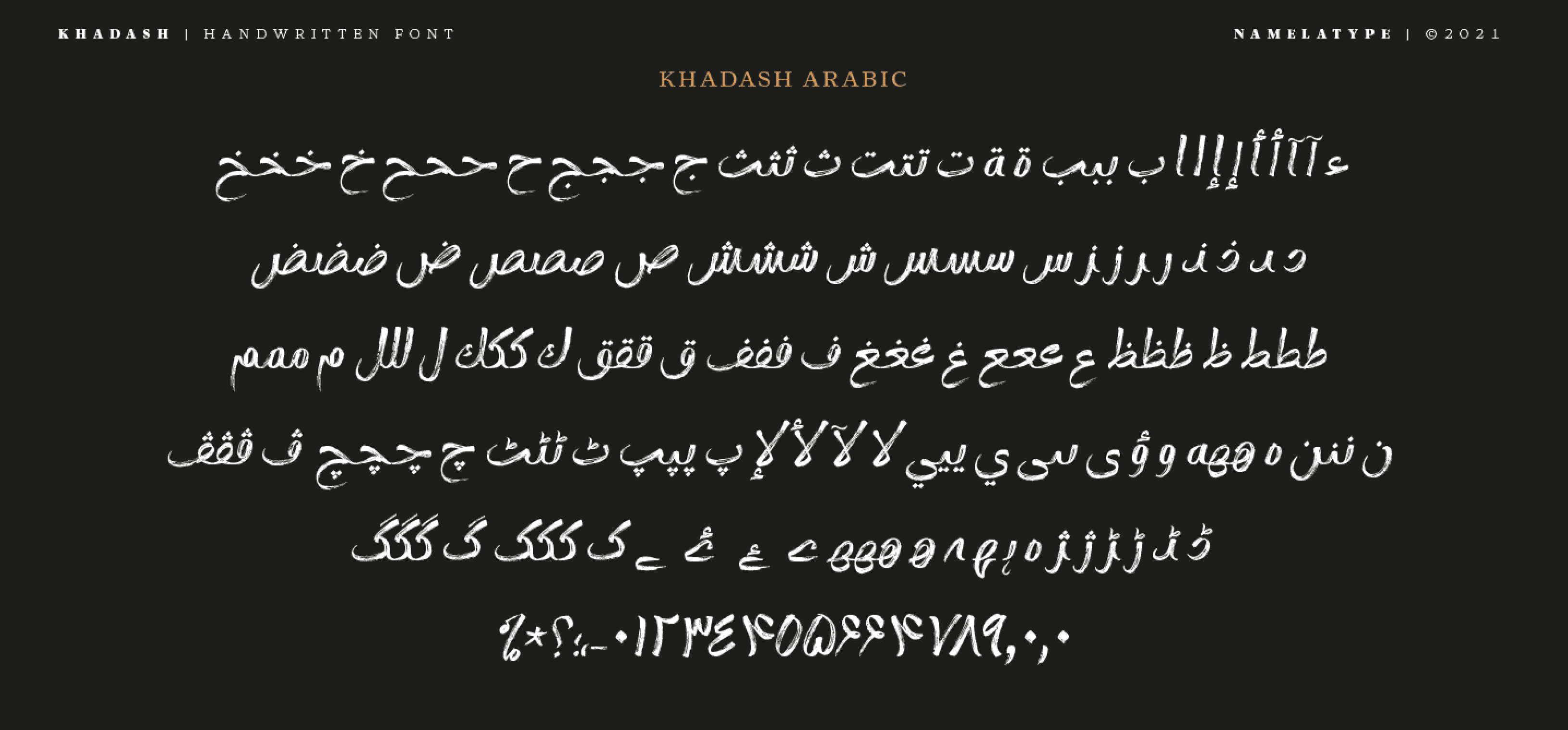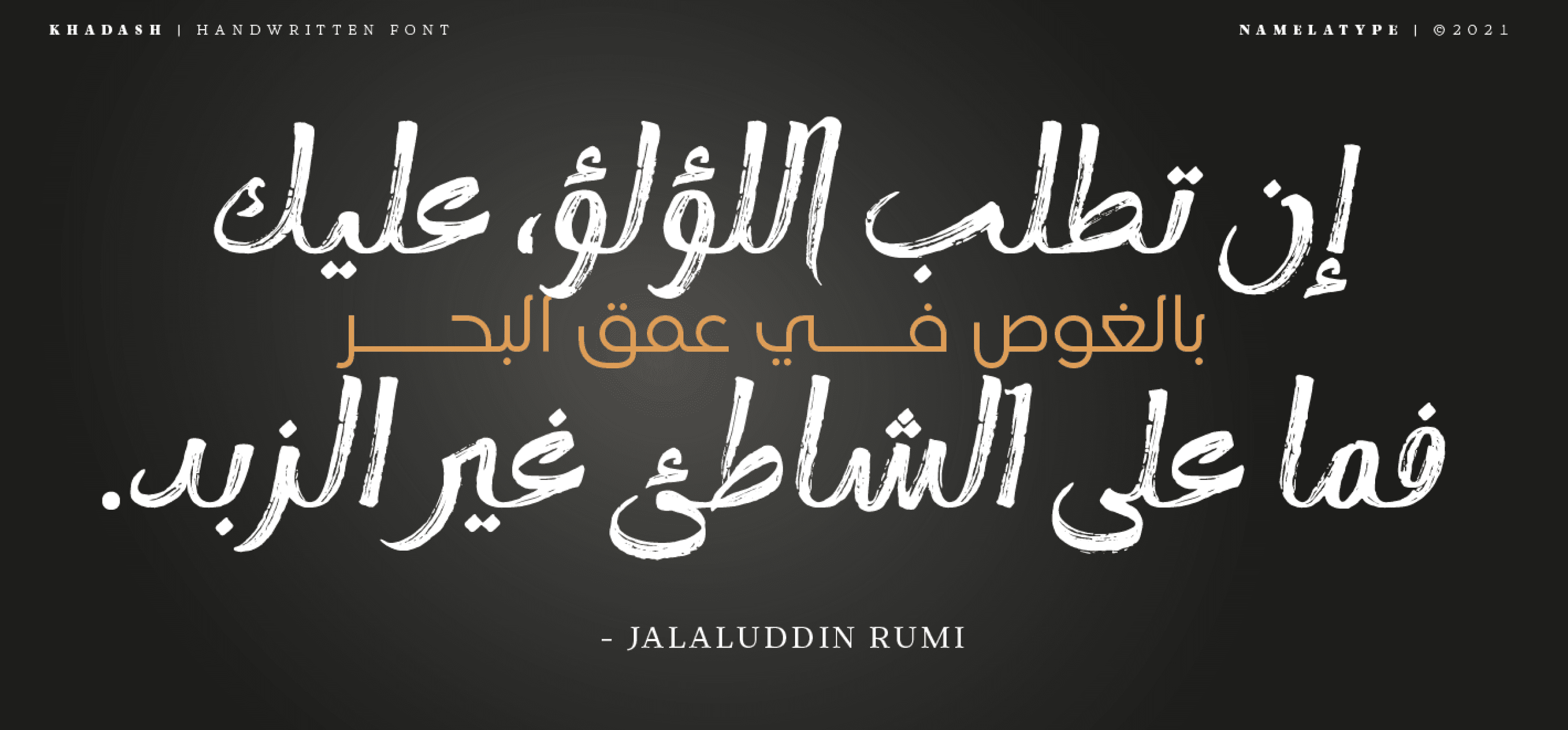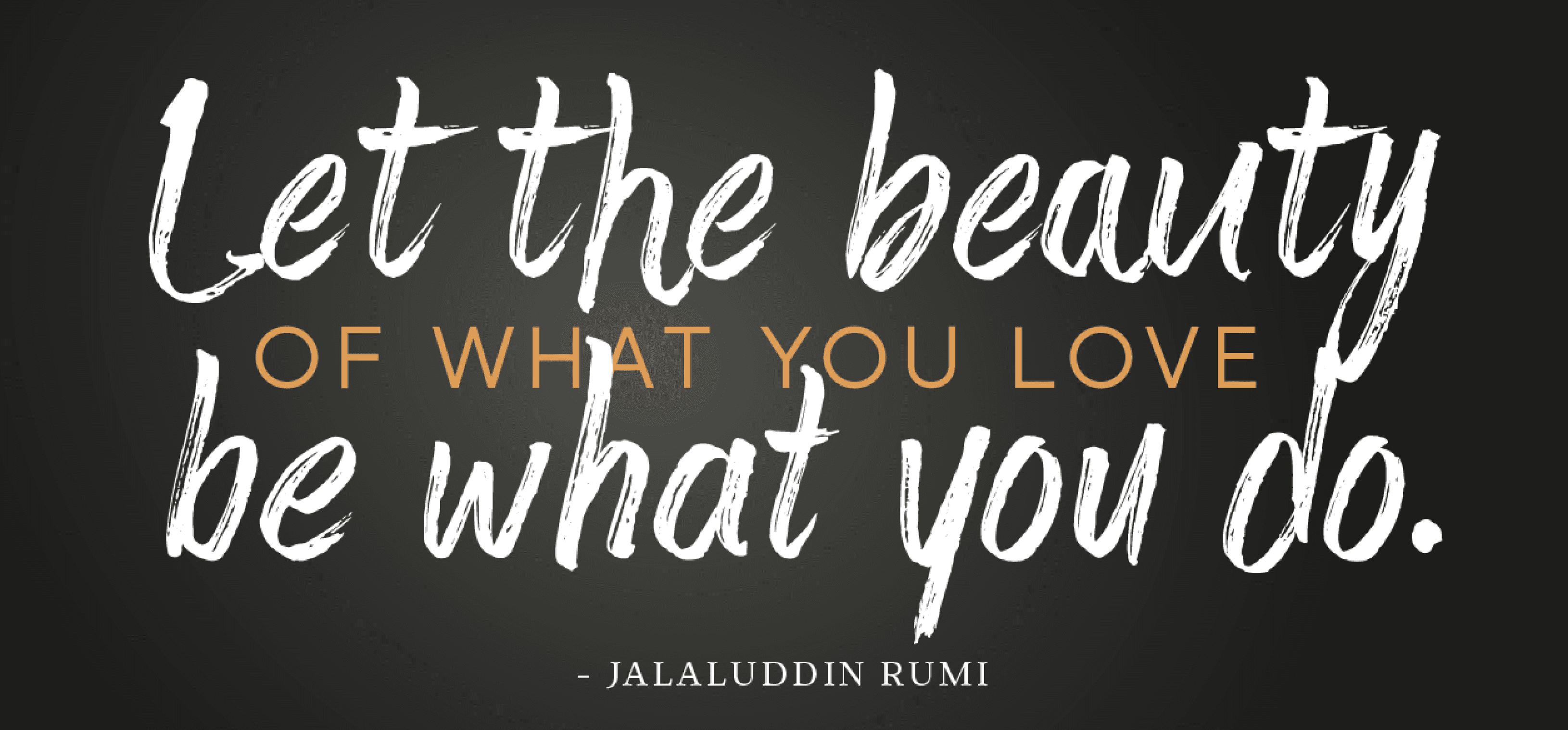
هو خط فرشاة عربي يتميز بمزيج آسر يجمع بين النص العربي والحروف اللاتينية، حيث تم دمج ضربات الفرشاة الطبيعية بشكل يُحاكي الخط اليدوي الحقيقي ببراعة.
يتضمن الجزء اللاتيني مجموعتين من الحروف:
مجموعة للاستخدام العادي
وأخرى للأنماط البديلة (Alternate Styling)